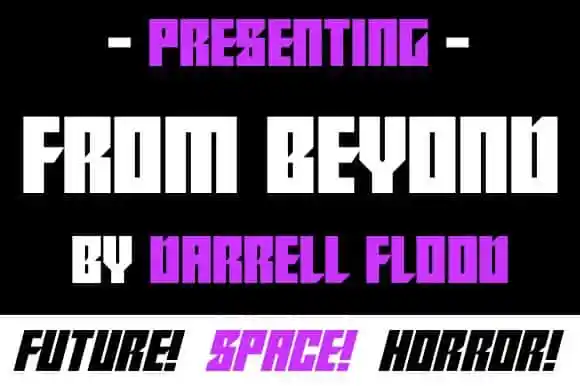
From Beyond Display Font – Download Grátis
A fonte “From Beyond Display Font” é uma escolha perfeita para aqueles que buscam uma maneira única de adicionar modernidade a seus projetos visuais, especialmente para áreas como design gráfico ou criação digital. Inspirada no estilo futurista e angular, ela combina elementos sci-fi com um visual clean e elegante. Ideal para títulos ou nomes de marca que precisam de destaque, esta fonte traz uma leveza e ar saudosista ao mesmo tempo moderno, perfeito para conjugar temas científicos, espaçonave ou qualquer outra ideia visionária em seu design. Com o estilo angular e edgy deste display font, você pode capturar a essência futurista de suas criações, tornando-as ainda mais memoráveis e inovadoras. Com um visual tão distintivo e uma aplicação tão simples, “From Beyond Display Font” é uma ótima escolha para quem busca agregar um toque único à sua obra, permitindo que seus projetos se destacuem da multidão. Seja você designer gráfico, editor de vídeos ou criador digital, esta fonte estará sempre pronta para ajudar a dar vida e personalidade aos seus trabalhos.